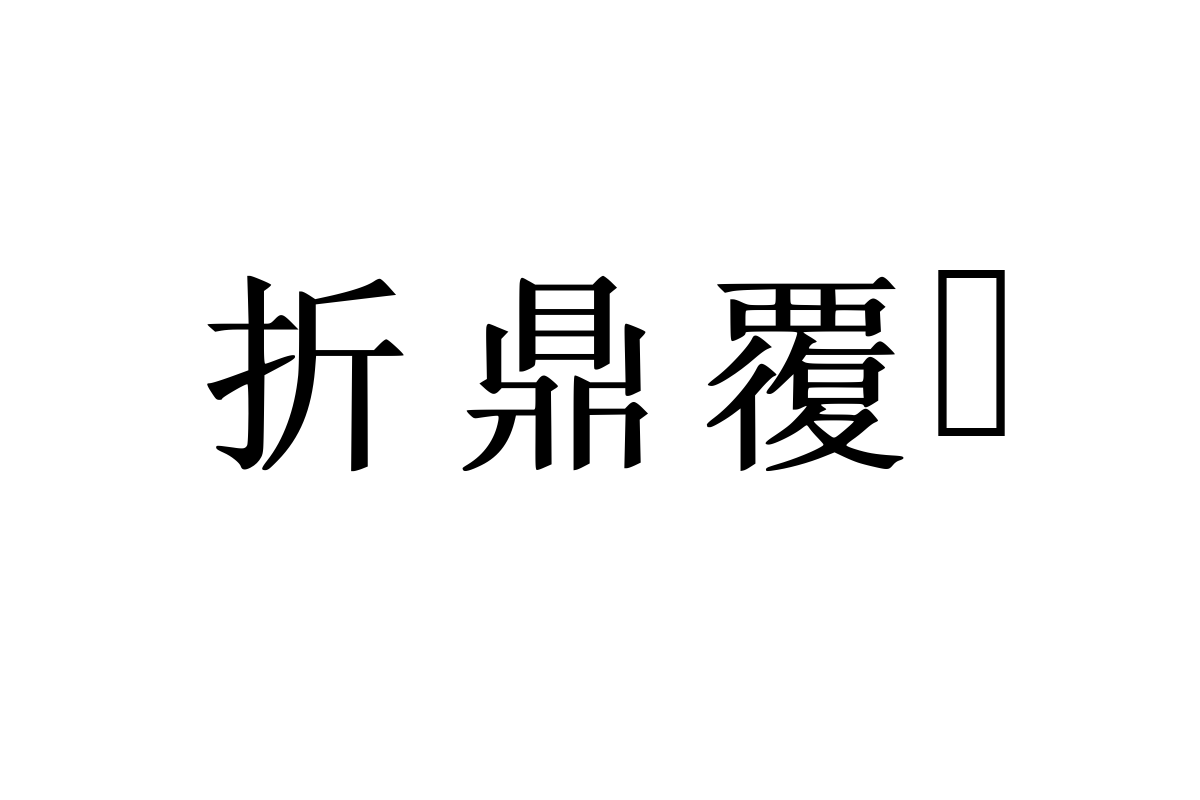
兰米新宋体加粗是一种字体,它的特点是在原有的兰米新宋体的基础上增加了一些粗细变化。这种字体通常用于标题、副标题等需要强调的部分,使得文字更加醒目。
兰米新宋体加粗的字体特点如下:
1. 字形饱满,结构紧凑,给人一种稳重的感觉。
2. 笔画粗细适中,既有兰米新宋体的清晰,又有加粗的突出效果。
3. 适用于需要强调的文字,如标题、副标题等。
4. 由于是加粗字体,所以在某些情况下可能会影响阅读体验,使用时需根据具体情况选择是否使用。